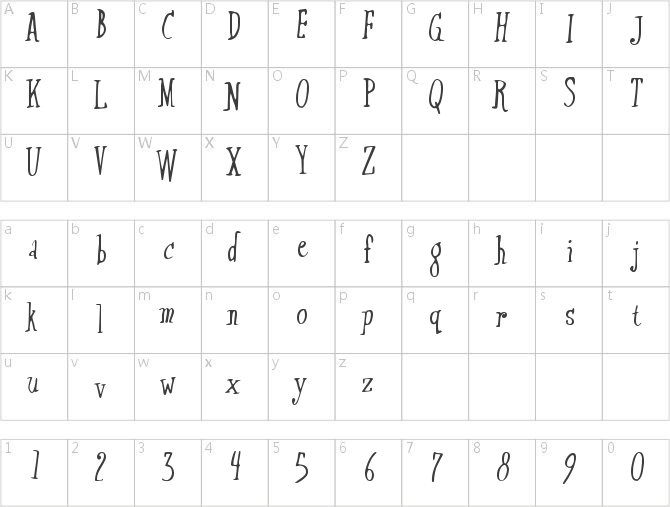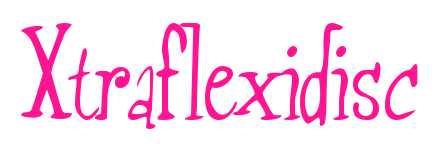
Xtraflexidisc 詳情頁
Xtraflexidisc
Xtraflexidisc介紹
Xtraflexidisc字體字庫是一款讓人賞心悅目、百看不厭的英文字體,適合各類廣告和產(chǎn)品包裝設(shè)計應(yīng)用,字體大小0.03MB,格式為ttf字體,上傳用戶是華大文化傳媒,作者/版權(quán)方為未知